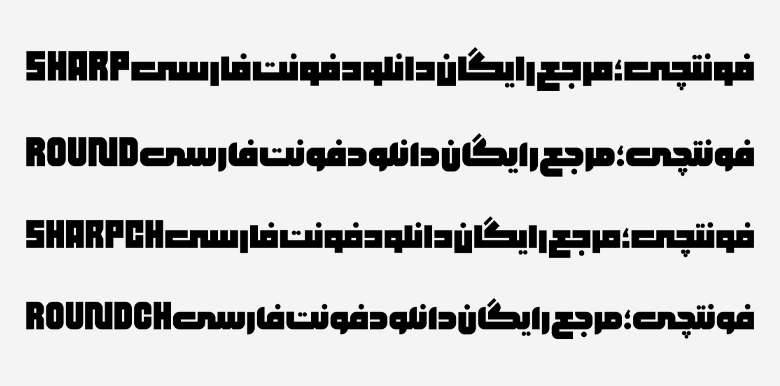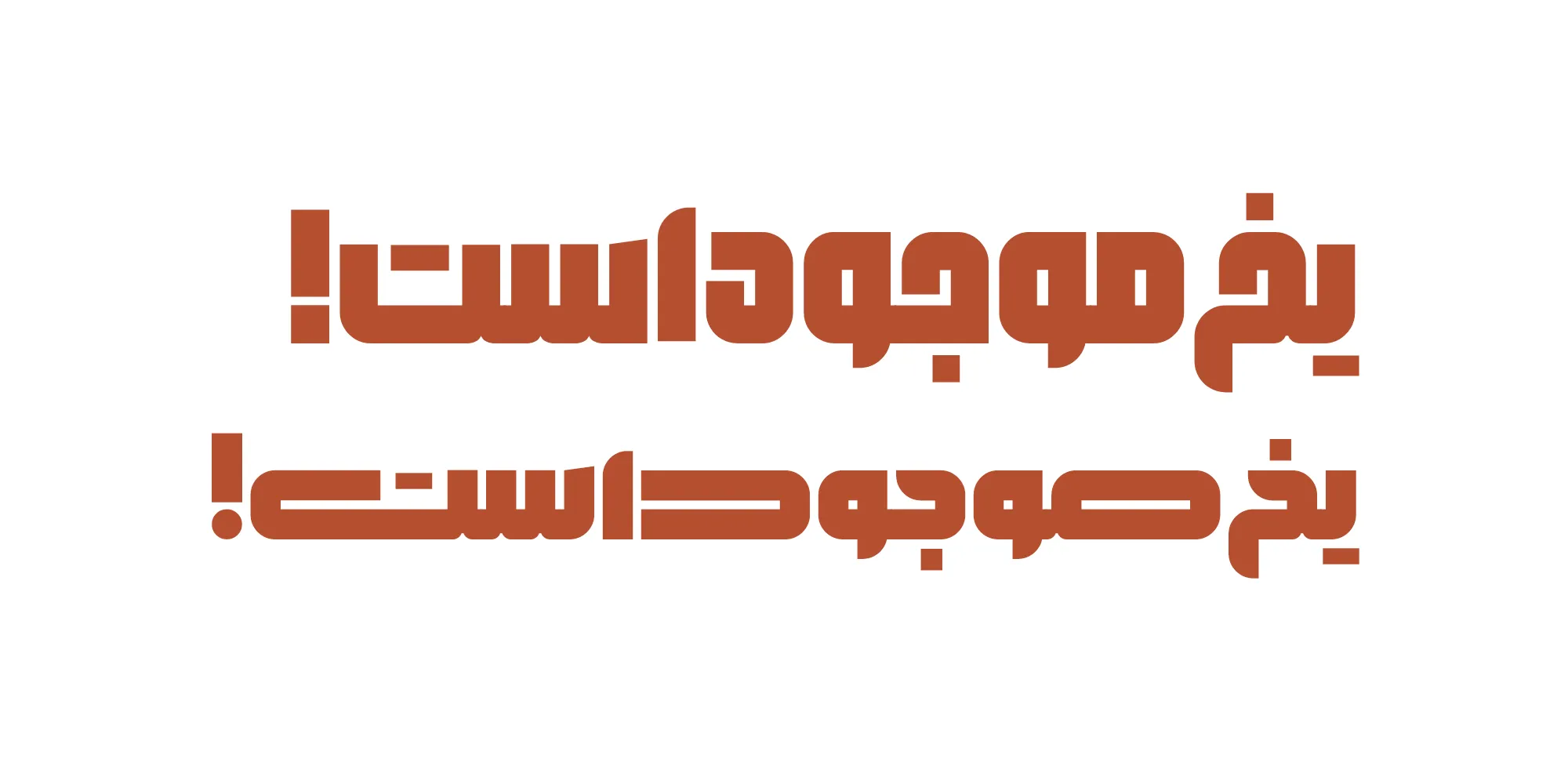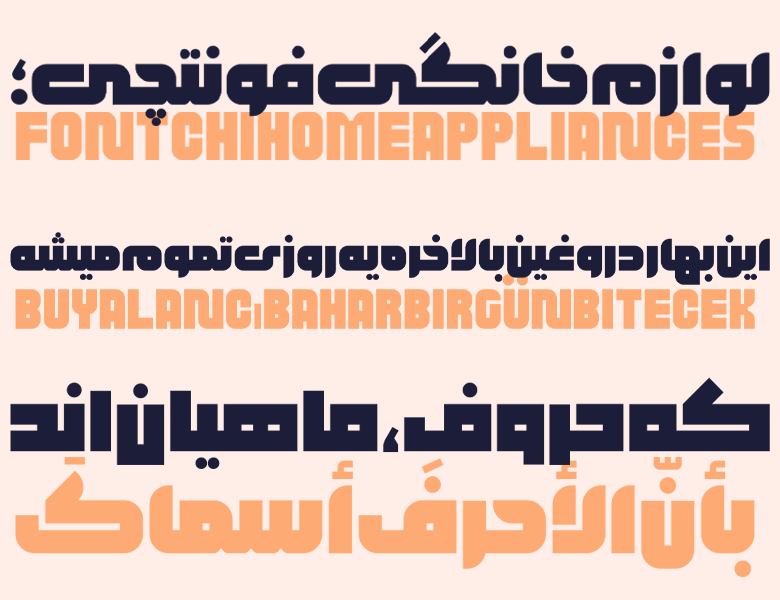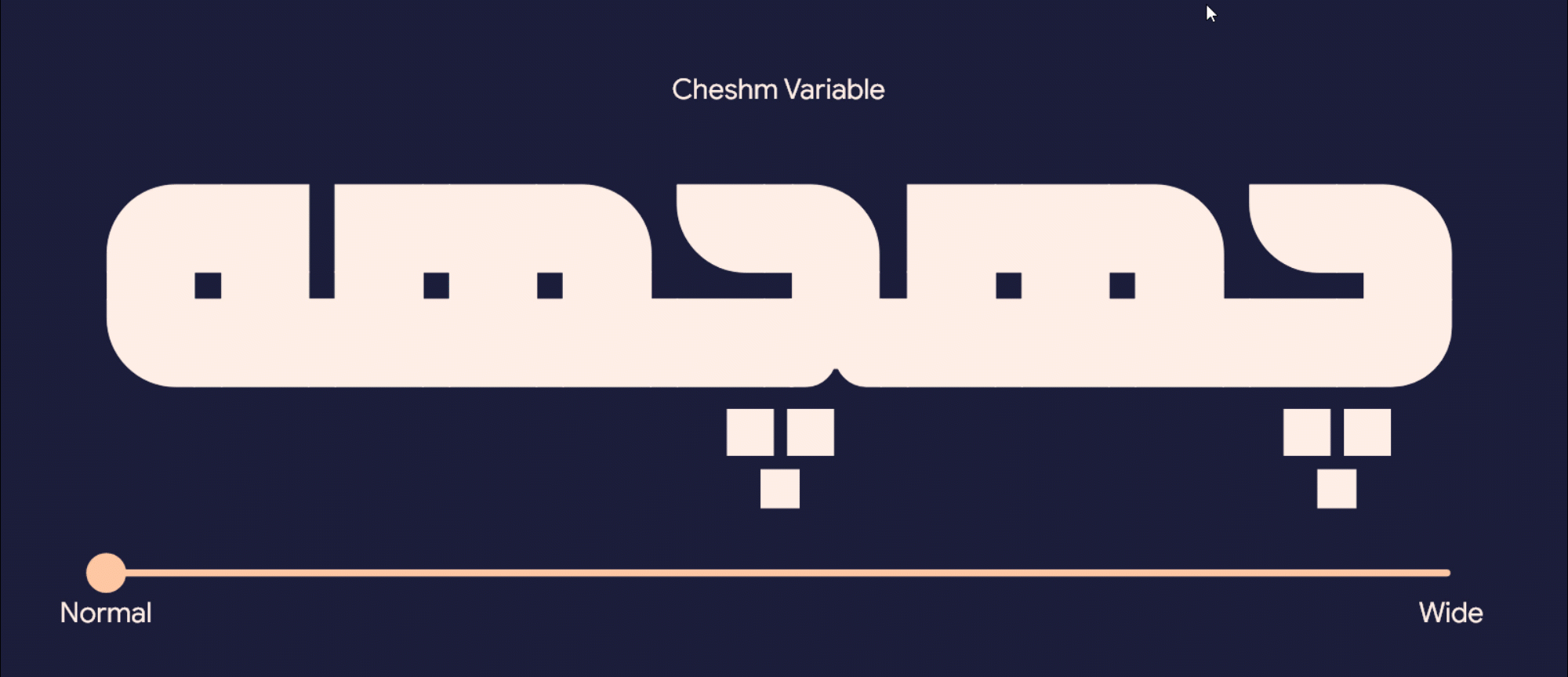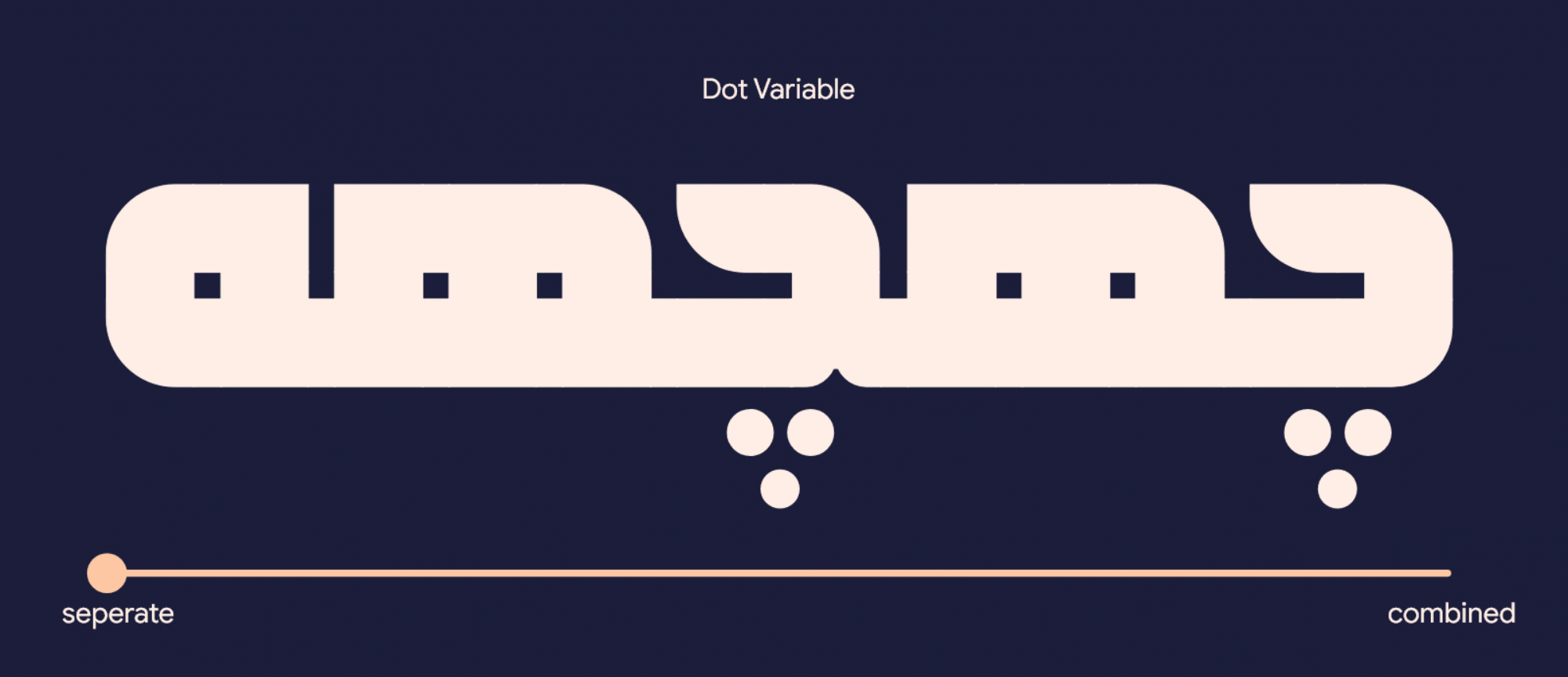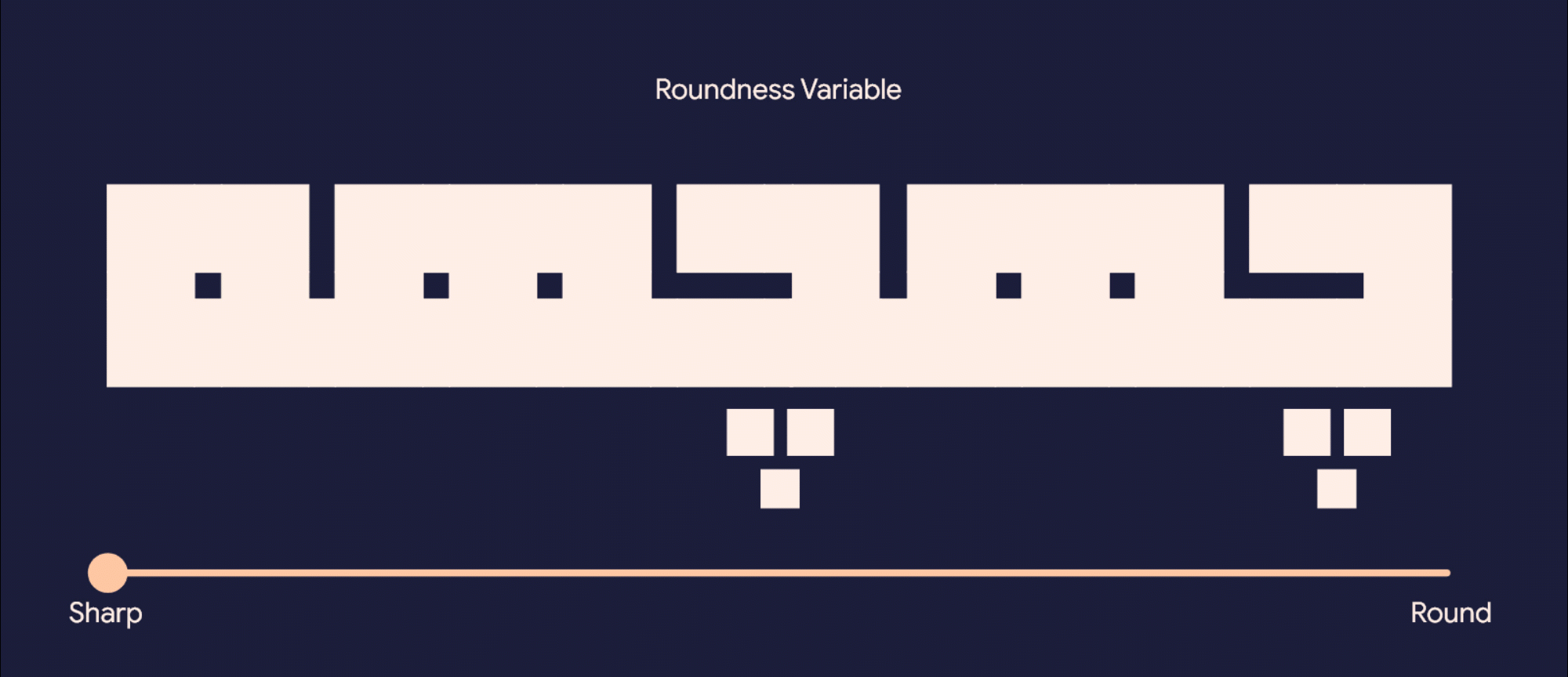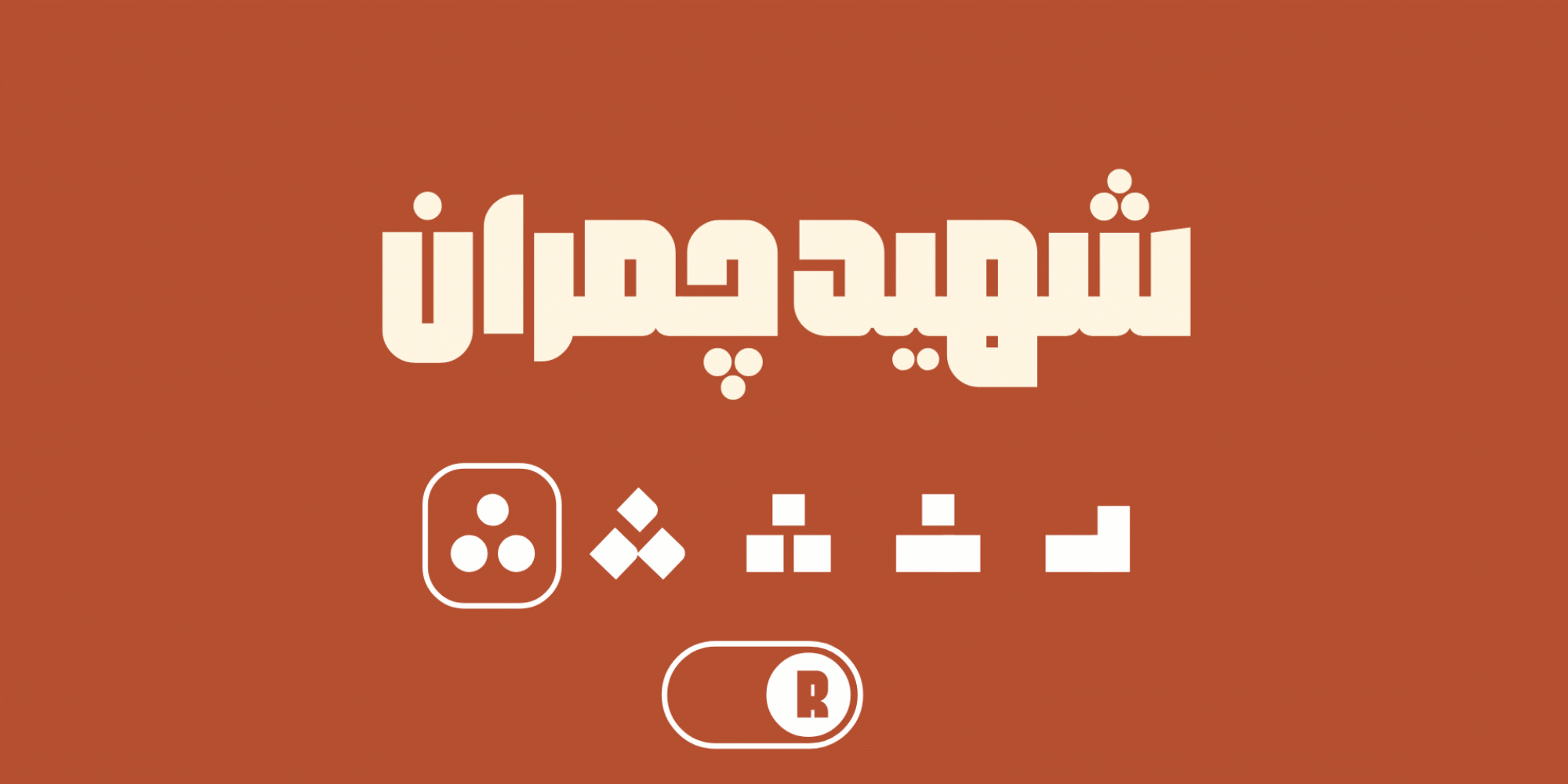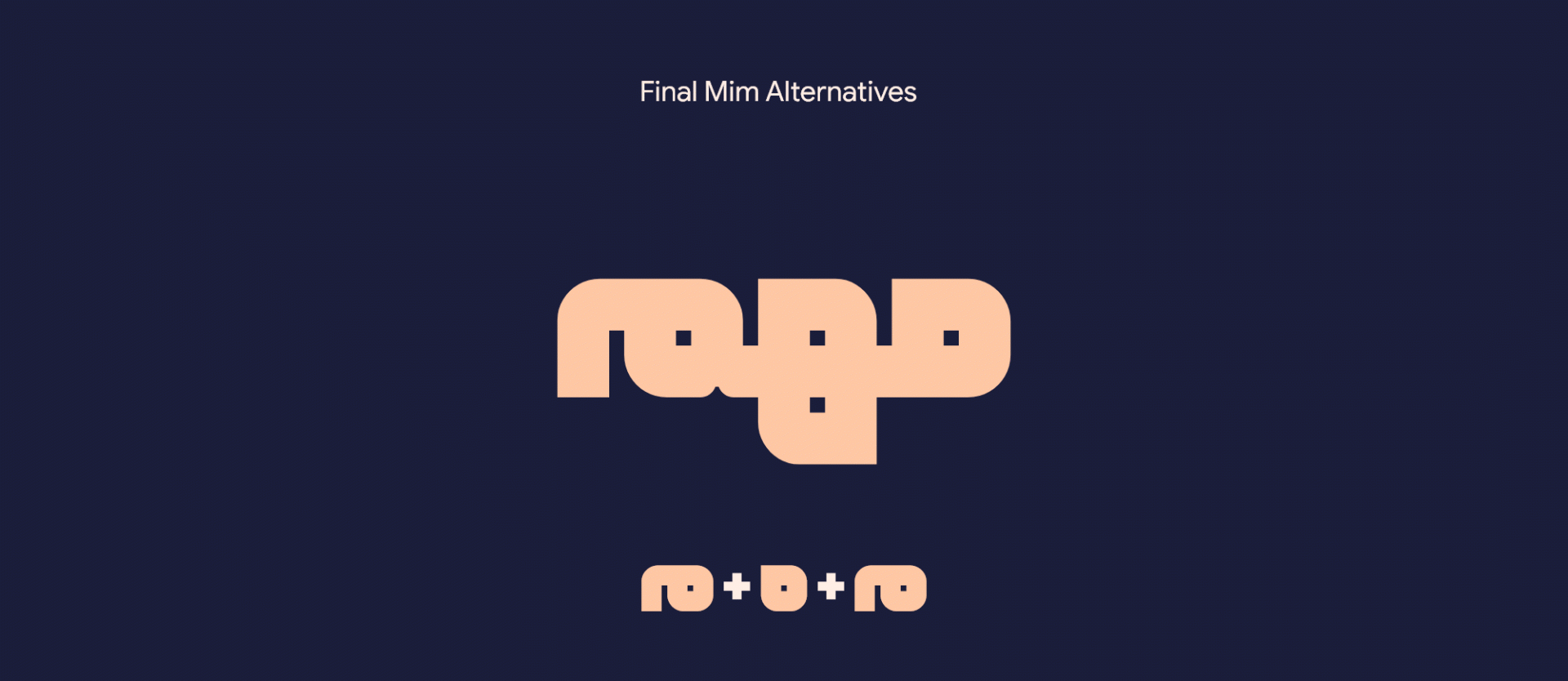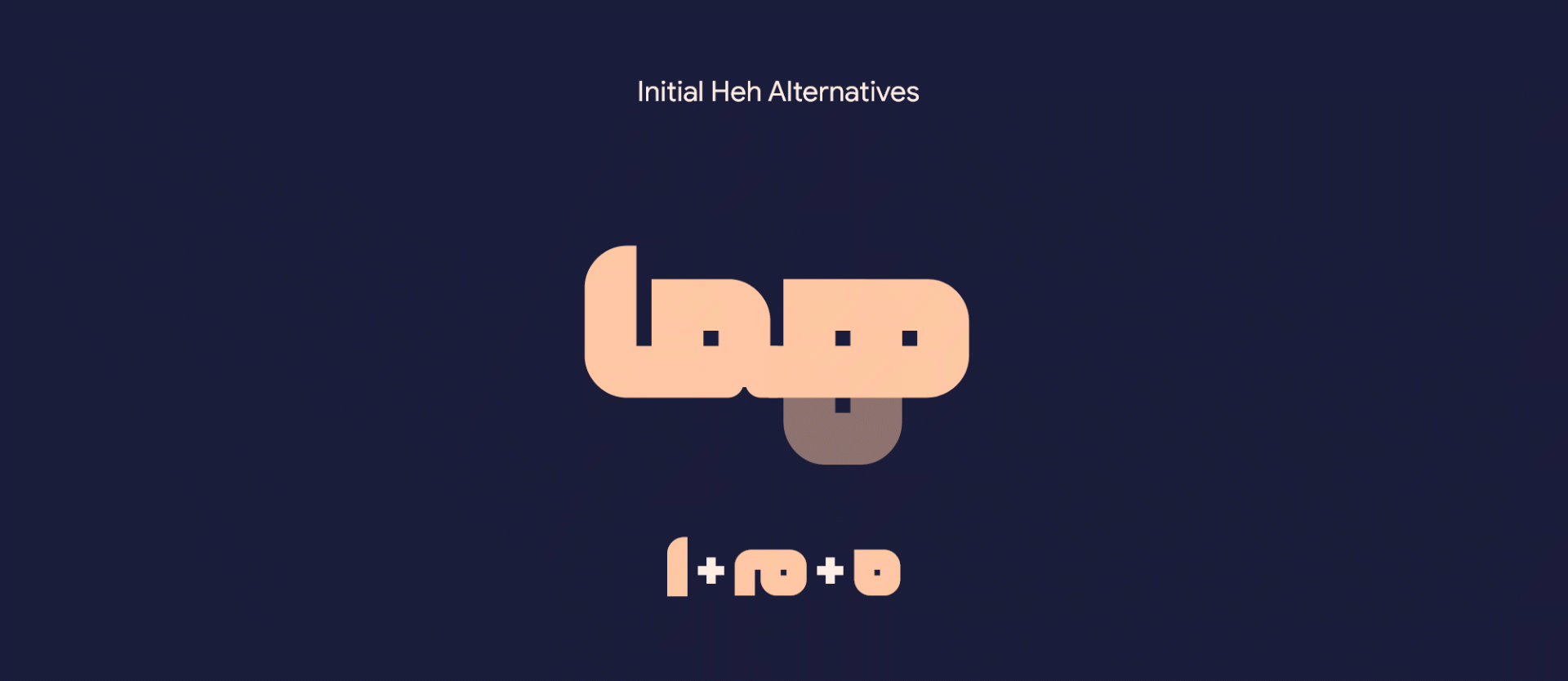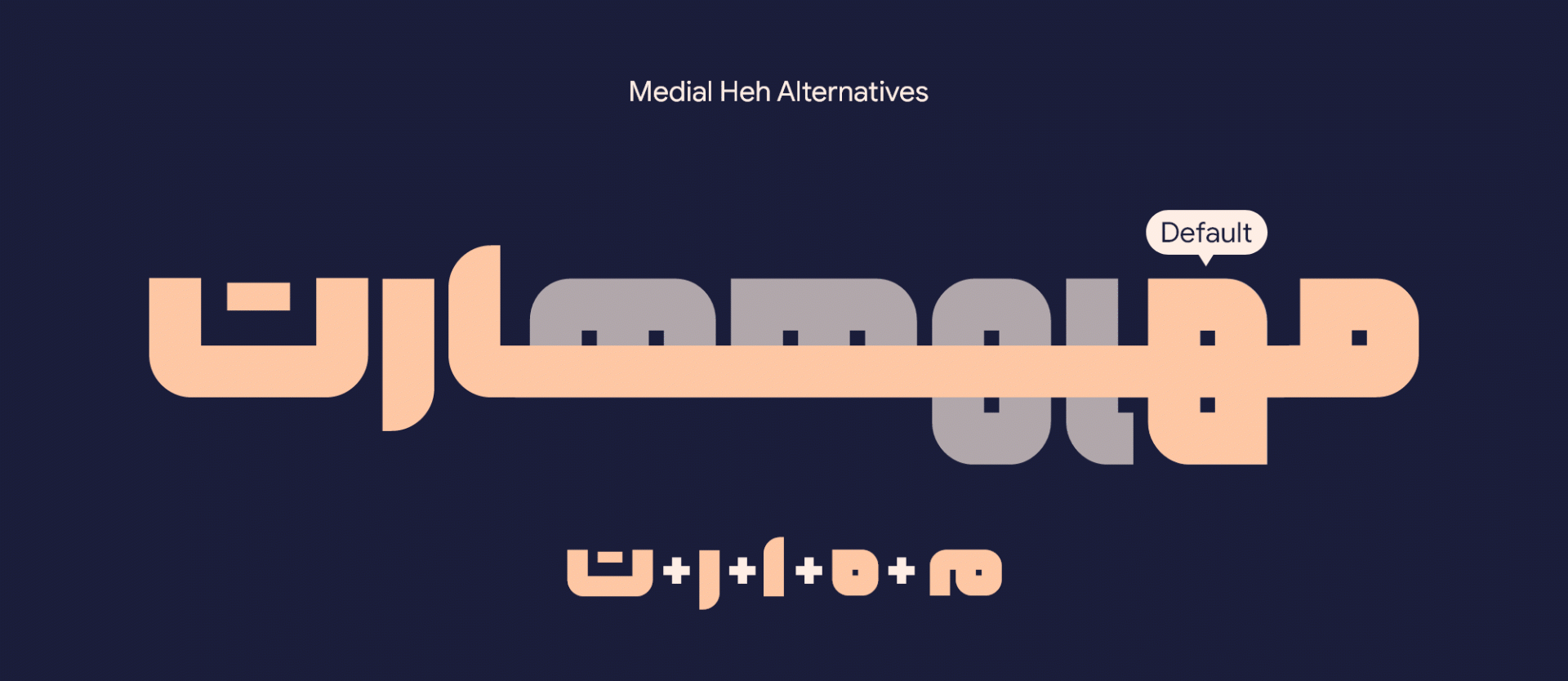
فونت بلوک (Block)
فونت بلوک (Block) الهام گرفته از ساختار مربع و مستطیل است که از دو خط کوفی بنایی و معلقی نیز وام گرفته شده است. این فونت فارسی که ساختاری کاملا هندسی و ضخیم دارد، مناسب عنوان و استفاده در محیطهای تبلیغاتی است که برای متنهای کوتاه و مواردی همچون شعارهای تبلیغاتی کاربردی خواهد بود.
طراحی این فونت توسط امیرحسین سعادتفر انجام گرفته و توسعه آن را امین عابدی انجام داده است. وزن این فونت طوری است که در دو سبک شارپ با گوشههایی تیز و سبک گرد با گوشههایی نرم و لطیف ساخته شده است. متغیر بودن فونت نیز امکان تغییر در گوشهها، چشمها و نقاط را در حروف در اختیار قرار خواهد داد.
حال در ادامه این نوشته از سایت فونتچی به نقد و بررسی این فونت زیبای نمایشی خواهیم پرداخت. با دانلود فونت بلوک میتوانید از ان برای طراحی انواع لوگوتایپ، چاپ روی بستهبندی محصولات، استفاده در عناوین و بهطور کلی هر طرح گرافیکی که نیاز دارید عناوین بیشتر مورد جلب توجه قرار گیرند استفاده کنید.
معرفی و بررسی فونت بلوک (Block)
ظاهر فونت بلوک در تمامی وزنهای آن آجری است. که بر اساس شکلهای مربع و مستطیل شکل گرفته است. تمامی استایلهای این فونت دارای ضخامت زیاد و ساختاری سیاه هستند که کنتراست بسیار بالایی هم دارند.
نوآوری و وجه تمایز فونت بلوک با سایر فونتهای فارسی از لحاظ فنی، در حروف جایگزین متفاوت در حروف ابتدایی میانه و انتهایی و کشیدگی کاراکترهای حرف کاف، گاف و دال میباشد.
استایل و وزن فونت بلوک
فونت بلوک فارسی هم یکی دیگر از معدود فونتهایی است که بر خلاف وزنهای رایج، بر اساس سبک و استایلی که دارد ظاهر متفاوتی را به شما خواهد داد. همین شکل خاص فونت استفاده از آن را برای متون طولانی محروم کرده است؛ اما به دلیل اینکه فونتی مناسب عنوان، تبلیغات و نمایشی است، میتواند در متنهای کوتاه جلوه و زیبایی خاصی به شما بدهد.
این فونت در ۴ استایل ساخته شده است که ر واقع دارای ۲ استایل اصلی به سبک شارپ(Sharp) و گرد(Round) است. اما هر یک از این سبکها دارای ساختارهای متفاوت از نظر نقطهگذاری و شکل حروف هستند.
در نسخه دوم فونت بلوک علاوه بر این دو استایل در سبک عادی یک سبک نسبتا فشرده یا Condensed به بسته اضافه شده که در این سبک برخی حروف بهجای امتداد در محور افق، با افزایش یک ردیف ارتفاع بیشتر امکان فشردهتر شدن افقی نوشتار را فراهم میکنند و این موضوع در مجموع میتواند دست طراح را در چیدمان هرچه بهتر بازتر کند.
سبک کاندِنسد (فشرده) سبکی رایج در بین تایپفیسهای لاتین بوده که به تازگی بهطور پختهتری وارد فضای نوشتار فارسی نیز شده است.
فونت بلوک با ترکیبی که از مربع و مستطیلهایی با گوشههای تیز یا گرد ایجاد شده است، در تمامی سبکهایی که دارد این ساختار را حفظ کرده است. نسخه وریبل این فونت هم در دسترس است که امکان کنترل بیشتری از نظر وزن، چشمها و سبک نقطهها به شما خواهد داد.
همانطور که بیشتر در صفحه دانلود فونت مربع ذکر کردم، فونت بلوک نیز مشابه آن فونت با توجه به ساختاری ضخیم و نمایشی که دارد، میتواند انتخاب مناسبی برای طراحی لوگو تایپ باشد. خصوصا در سبک استایل گرد که نرمی و دوستانه بودن بیشتری از خود نشان میدهد.
فونت بلوک فارسی علاوه بر این زبان از ۵ زبان دیگر پشتیبانی میکند که در مجموع شامل ۶ زبان فارسی، عربی، انگلیسی، کردی، اردو و ترکی میشود.
در تمامی زبانهای لاتین و خاورمیانهای این فونت کاراکترها، اعراب و نقطه گذاری هر فونت بسته به وزن انتخابی شارپ و گرد که هر یک در دو حالت وجود دارند طراحی شده تا متنهایی یکپارچه در همه زبانها داشته باشید.
فونت متغیر بلوک با ۳ قابلیت مختلف
فونت حرفه ای بلوک بر خلاف نسخه متغیر (Variable) که بیشتر فونتها دارند، دارای ساختار پیچیدهتری است که علاوه بر تغییر وزن، امکان تغییر بخشهای دیگری از حروف را نیز به شما خواهد داد که به طور کلی شامل ۳ بخش زیر میشود.
حالت اول: مربوط به تغییر چشم است که با نام Cheshm Variable شناخته میشود. در این حالت همانطور که در تصویر بالا مشاهده میکنید حروفی همچون «ص، ض، ط، ظ، ـع، ـغ، ف، ق، م، و، ه» که دارای چشمی هستند، این امکان را دارند که بتوانید چشمیها را به صورت عرضی با اندازه بزرگتری از حالت معمول تنظیم کنید.
حالت دوم: مربوط به تغییر ظاهر نقطهها در چهار حالت مختلف است. در نسخه متغیر فونت بلوک که با نام Dot Varible شناخته میشود، مثل تصویر بالا میتوانید نقاط حروف را در حالتهای گرد، ۴ گوش رند شده، ۴ گوش و چسبان به هم تنظیم کنید.
حالت سوم: در این حالت هم که با نام Roundness Variable شناخته میشود، میتوانید میزان گردی حروف (خمیدگیهای حاشیه) را تنظیم کنید که در ساختار مربعی ۴ گوش باشند یا اینکه دارای زوایای گرد در بخش تقاطعات هر حرف باشد.
پشتیبانی از ۵ حالت نقطهگذاری
در نسخه دوم فونت بلوک شاهد ایجاد تغییراتی در حالت نقطهگذاری نیز هستیم. در تمامی سبکها و وزنهای این قلم پشتیبانی از پنج حالت نقطهگذاری نیز تعبیه شده که میتوانید با دانلود فونت بلوک برای فتوشاپ از طریق تنظیمات اپنتایپ این نقاط را بدون انجام کارهای گرافیکی پیچیده مطابق با تصویر زیر تغییر دهید.
علاوهبراین اگر از نسخه وریبل این قلم استفاده میکنید امکان تغییر شکل نقاط از طریق کدهای CSS نیز در محیط وب فراهم شده است که با استفاده از فایل راهنما میتوانید آنها را تغییر دهید.